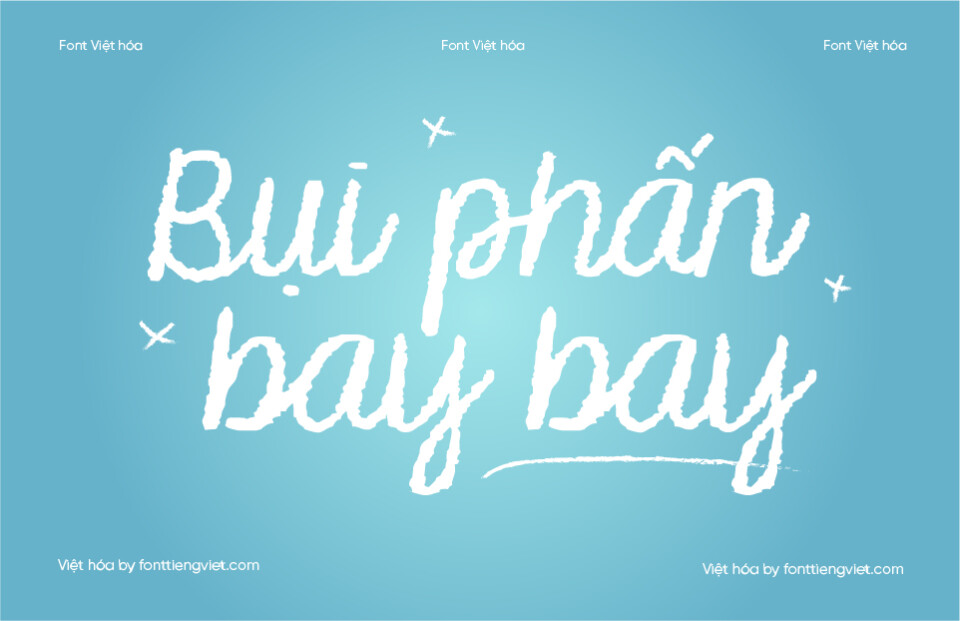
Giới thiệu về bộ Font Việt hóa 1FTV VIP Makes You Stronger – Phấn
Trong môi trường học đường, việc lựa chọn Font Chữ phù hợp đóng vai trò quan trọng trong việc truyền tải thông điệp và cảm hứng học tập. Font Việt hóa 1FTV VIP Makes You Stronger – Phấn là một lựa chọn tuyệt vời dành cho các thầy cô và học sinh. Đây là bộ font mang phong cách bảng đen viết phấn đầy mộc mạc, giúp các bài giảng điện tử hay báo tường trở nên gần gũi và sinh động hơn bao giờ hết.
Đặc điểm nổi bật của bộ font chữ phấn bảng
Bộ Font Việt hóa 1FTV VIP Makes You Stronger – Phấn mô phỏng chân thực những nét vẽ bằng phấn trên nền bảng xanh truyền thống. Với các nét thanh nét đậm tự nhiên, font chữ này tạo cảm giác như được viết tay thủ công, mang lại sự ấm áp và tính giáo dục cao. Đặc biệt, bản Việt hóa đã được tối ưu hóa đầy đủ các dấu tiếng Việt, đảm bảo không bị lỗi hiển thị khi soạn thảo nội dung dài.
Ứng dụng thực tế của Font Việt hóa 1FTV VIP Makes You Stronger – Phấn
Sử dụng trong giảng dạy và thiết kế học đường
Thầy cô có thể sử dụng font này để thiết kế slide PowerPoint, làm tiêu đề cho các phiếu bài tập hoặc trang trí không gian lớp học. Sự xuất hiện của Font Việt hóa 1FTV VIP Makes You Stronger – Phấn giúp học sinh cảm thấy thân thuộc, từ đó tăng khả năng tập trung vào nội dung bài học. Ngoài ra, các bạn học sinh cũng có thể dùng font để làm tập san, kỷ yếu hoặc thiệp chúc mừng thầy cô.
Lưu ý khi sử dụng font chữ
Để đạt hiệu quả thẩm mỹ tốt nhất, bạn nên kết hợp font với các tông màu sáng như trắng, vàng nhạt trên nền tối. Điều này giúp tái hiện hoàn hảo hiệu ứng phấn viết bảng, tạo nên phong cách thiết kế Retro ấn tượng và chuyên nghiệp.